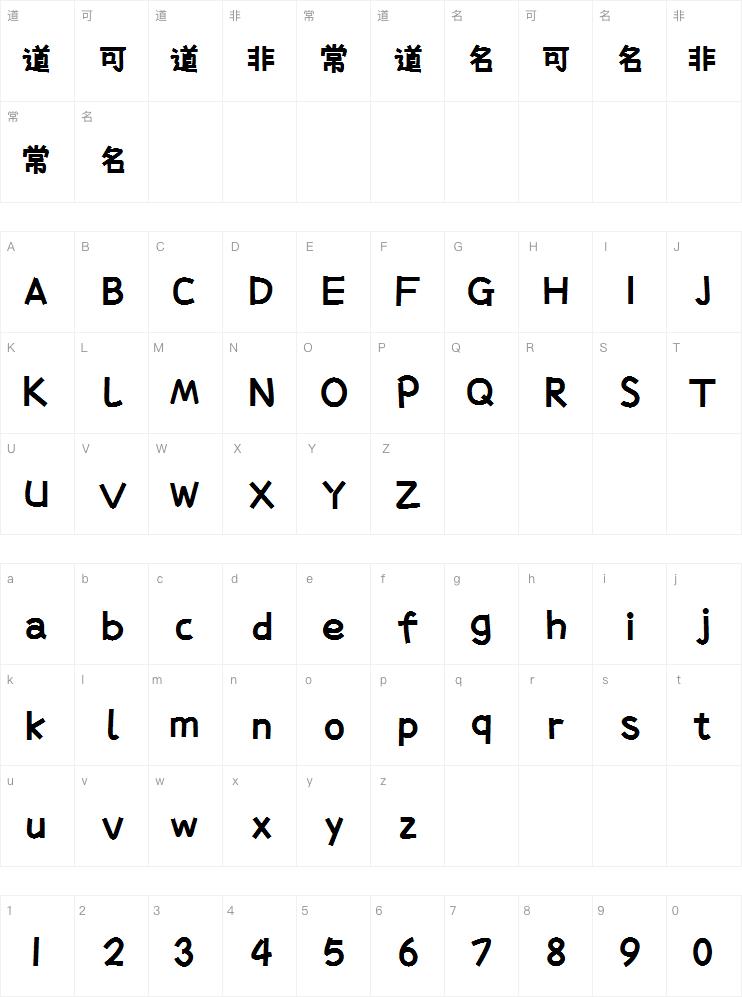
锐字潮牌公仔POP简是一款融合了经典卡通元素的风格率真的创意POP手写体。字体整体灵动活泼,字形大小随笔画数量波动,整体形状随结构形式或略扁或略长,在排版时可以使版面效果生动有趣,又不过度随机显得太随意。笔画等粗,灰度适中,整体造型表现出公仔玩具般的圆润俏皮,尤其是钩笔,向上翘起显得Q弹可爱。适用于各种品牌包装、广告排版、综艺节目字幕和趣味营销活动等。